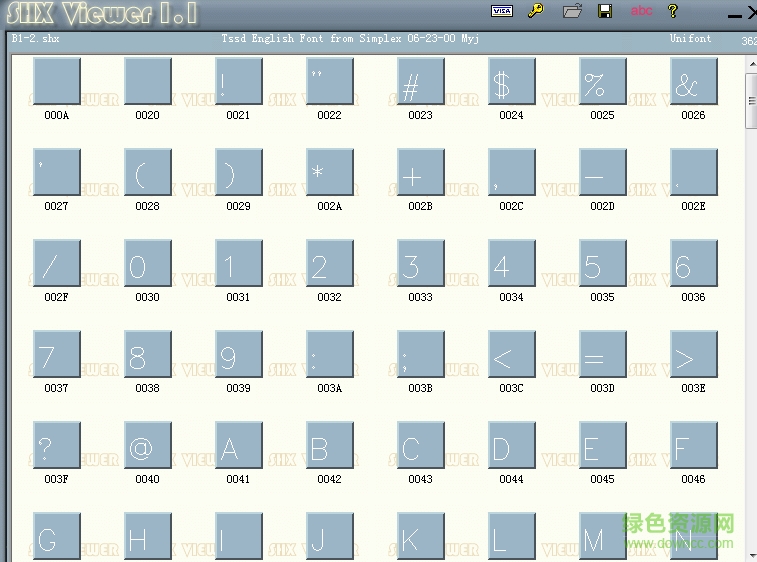
B1-2.shx字體是一款專(zhuān)為解決用戶(hù)打開(kāi)文件,文字不顯示,或者提示找不到文件的朋友打造的一款cad字體,需要的朋友趕緊來(lái)綠色資源網(wǎng)下載吧
該字體比較細(xì),很多設(shè)計(jì)院都是用這款字體喲,打不開(kāi)文件的朋友在本站下載替換下字體就可以解決了。